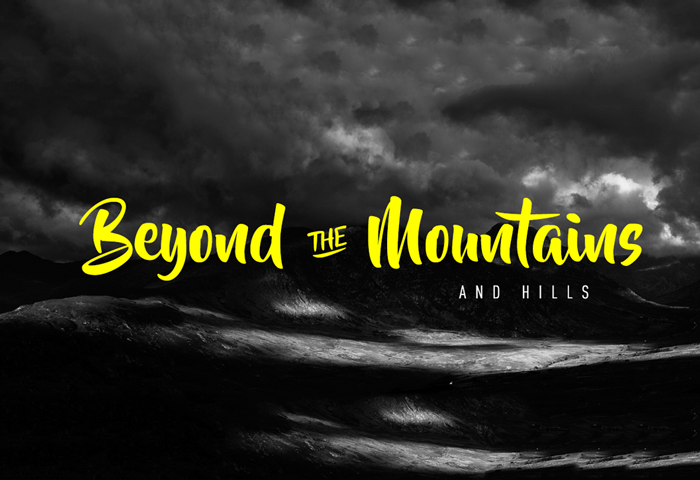
Descubra uma nova fonte chamada Beyond The Mountains para seu projeto gráfico. Desenvolvida pelo designer Hamilton, esta fonte Brush é ideal tanto para trabalhos artísticos quanto comerciais. Suas alternativas de caratê, ligaturas variadas e swashes permitem criar um estilo único que se destaca em qualquer design. Para aqueles que buscam uma licença comercial, a versão comercial está disponível aqui: http://www.stereo-type.fr. Com essa fonte incorporada nos PDFs, você terá mais flexibilidade para editar e personalizar seus projetos conforme necessário. Ainda não testou Beyond The Mountains? É hora de explorar suas possibilidades criativas e artísticas!